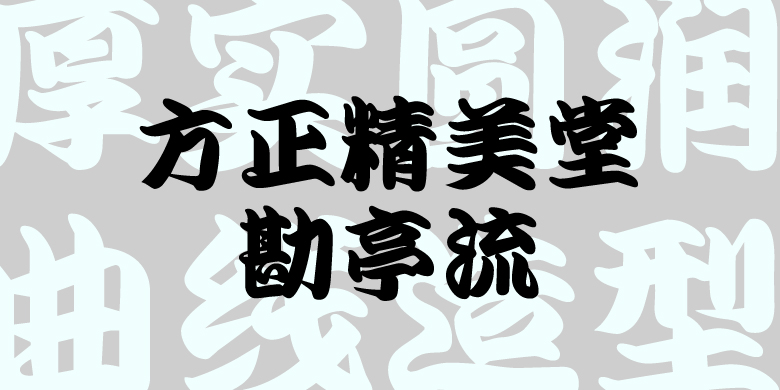
方正精美堂勘亭流
日本精美堂
创意字体
方正精美堂勘亭流是方正电子于2025年从日本引进的一款创意字体,该字体是日本江户文字中最具代表性的字体类型,由戏剧界人士冈崎屋勘六设计,其名称来源于设计者的别号“勘亭”。该字体以笔画厚实圆润、全曲线造型为特征,最初应用于歌舞伎的招牌或节目表设计,寄托观众流连忘返的期许。这类字体在日本传统风格的设计中备受青睐,广泛应用于招牌、标题和包装等。